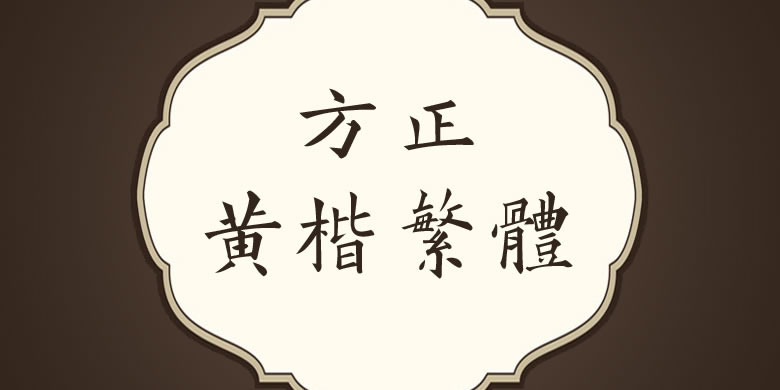
品牌:字酷堂 设计师:过中运,乌新丽发行时间:2017字库编码:港台地区(BIG-5)、大陆简体(GB2312-80)分类:常规书写·毛笔
这款字体复刻自《黄自元间架结构摘要九十二法》等黄自元书法作品。《间架结构摘要九十二法》至今仍是书法入门的常用教材之一。黄自元(1837–1918),字敬舆,号澹叟,湖南安化县龙塘乡人,清末书法家,实业家。生于道光十七年(1837),清同治六年(1867)举于乡,次年殿试列第二(榜眼),授翰林院编修。曾任顺天乡试同考官和江南乡试副考官。民国7年(1918)病逝。曾临摹《间架结构摘要九十二法》书帖,为该书的推广做出了重要贡献。